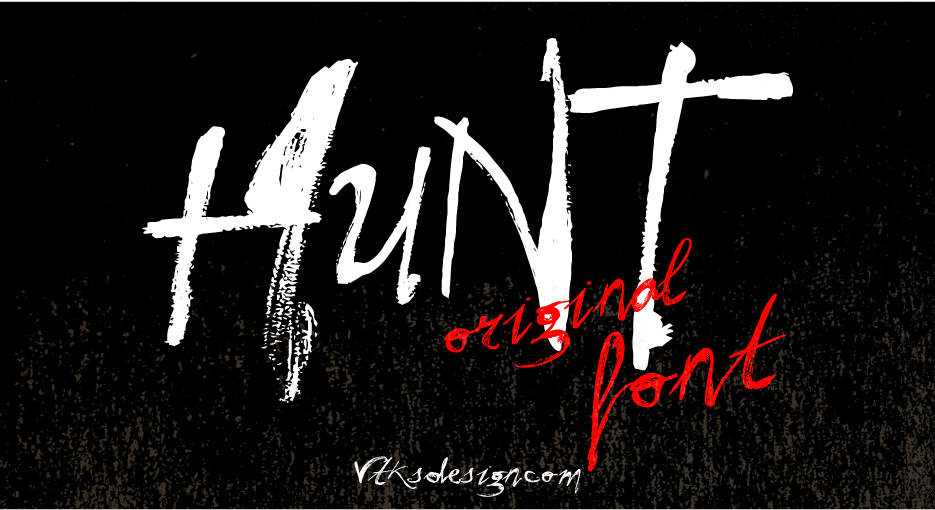
Vtks Hunt Font – Download Grátis
A Vtks Hunt Font é uma elegante fonte brush que se destaca em sua categoria. Inspirada em letras grafadas a mão, ela traz consigo um charme único e original que complementa perfeitamente projetos de design gráfico para negócios. Com seu designer, Hamilton, dedicando-se ao detalhe, essa fonte oferece uma variedade de estilos e tamanhos ideais para aplicação em materiais digitais ou impressos. Ela é perfeita para designers que buscam um estilo distintivo para seus projetos. PayPal receitas são sua autorização clara para usar nossa fonte em propósitos comerciais. Para adquirir uma licença, basta acessar o link fornecido: [Aqui está o link](https://exemplo.com/). Além disso, é importante mencionar que todas as informações aqui fornecidas são de referência e devem ser confirmadas diretamente pela fonte. É um prazer compartilhar este recurso com você e certamente esperamos ter a oportunidade de contribuir ainda mais para o seu trabalho de design.